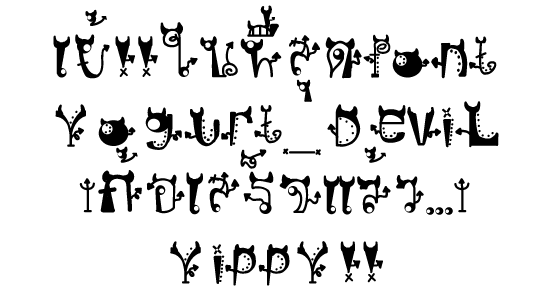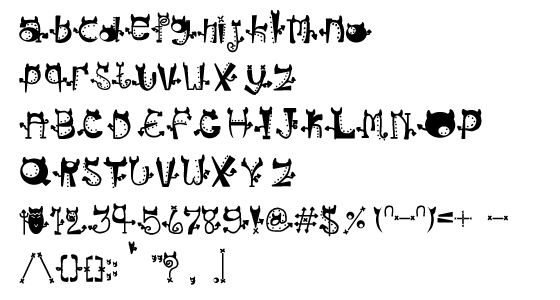
ฟ๐นต์YOGURT_DEVILเรียบร้อยแล้วค่ะ
นี่คะ
ทำตั้งแต่เช้าเพิ่งมาเสร็จเอาตอนนี้
ในที่สุดก็สำเร็จ
หลังจากตั้งกระจู่มาหลายอัน :22:
ช่วยดูกันหน่อยนะคะ
ว่าแบบนี้เอาขึ้นเว็บได้ไหม??
ไปนอนแล้วนะคะ เมื่อย นั่งเก๊กมือตั้งนาน
แต่ก็ได้ผลงานชิ้นแรกแล้ว ดีใจๆ :33:
มีให้แก้ไขตรงไหนบอกด้วยนะคะ :22:
เช็คไม้ไต่คู้ ด้วยครับ
มันอยู่ข้างหน้ามากไปหน่อย
:22:ไปแก้ไขเรียบร้อยแล้วค่ะ
ก็ ไม่ใช่ ก้อ นะคะ  :33:
ส เสือ กับ ล ลิง แยกไม่ค่อยออกนะค่ะ  :42:
ตายล่ะ ลืมตัว :25:
เอาแบบอังกฤษมาให้ดูก่อนนะคะ
น่ารัก  :25:
(เพ่งตั้งนานตรงคำว่า ก้อ เนี่ย  :42:)
fคล้ายกับpไปหน่อยครับ
ไม้เอก ติดกับ สระอี ไปหน่อยนะ
ฟอนต์น่ารักจัง  :42:
ตกลงว่าได้ฟอต์มาแล้วนะ เดี๋ยวทำ preview เป็น flash ให้นะ